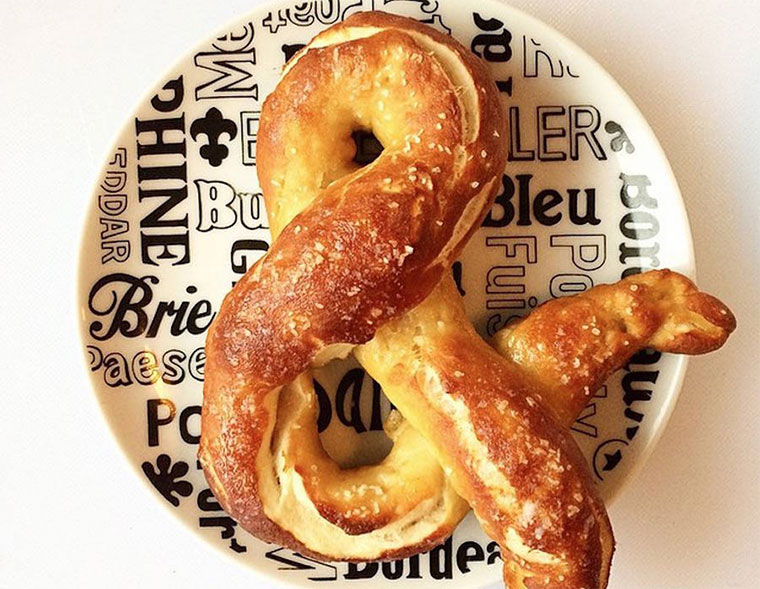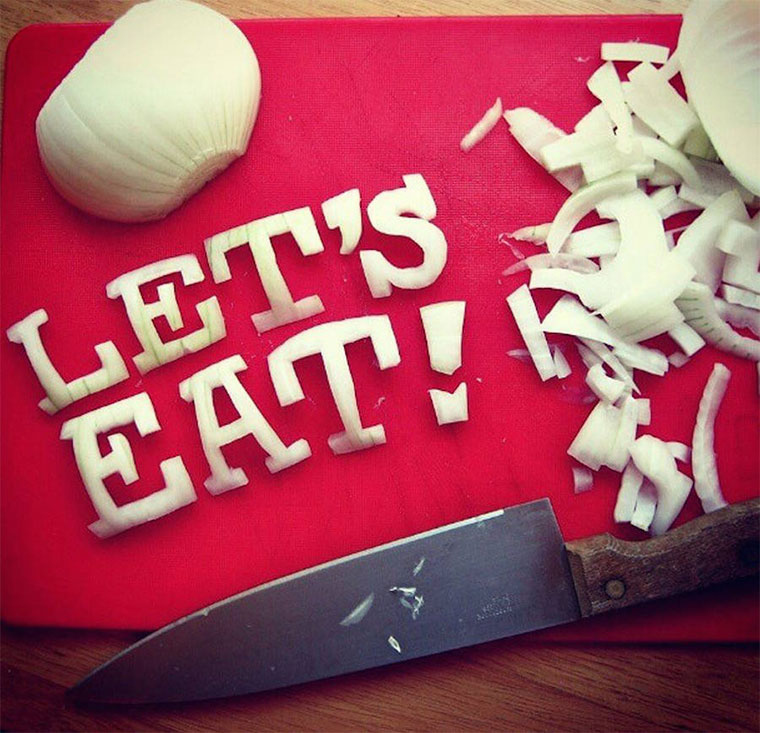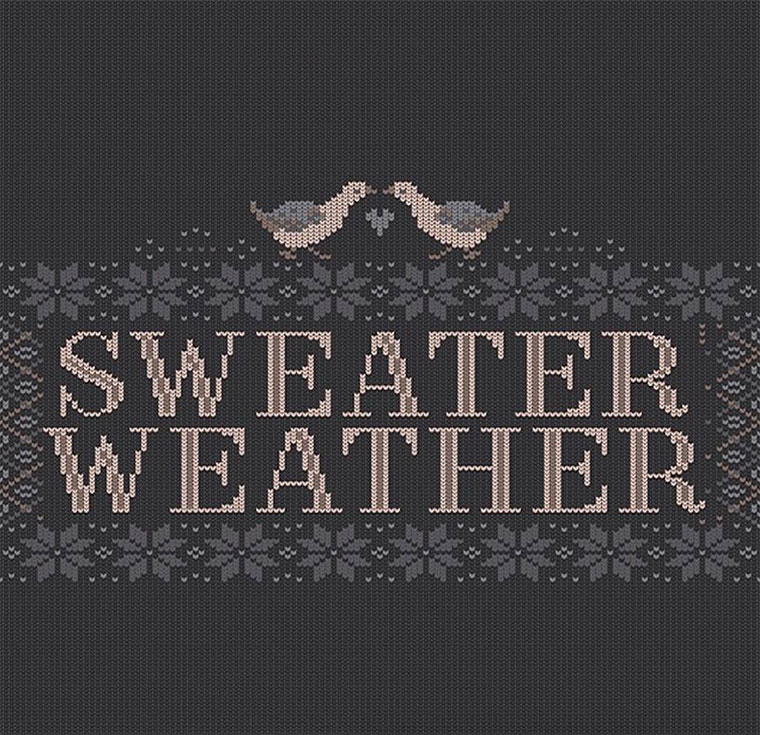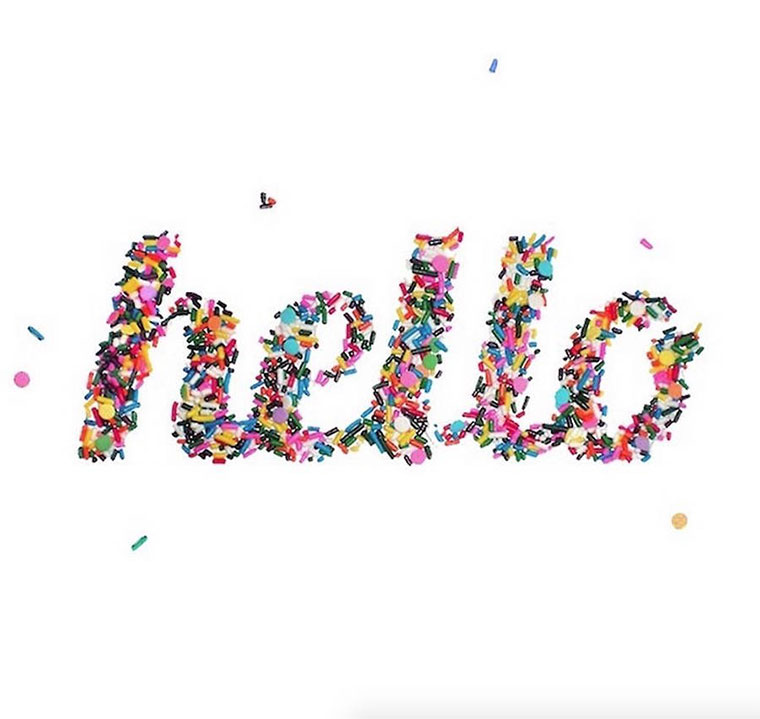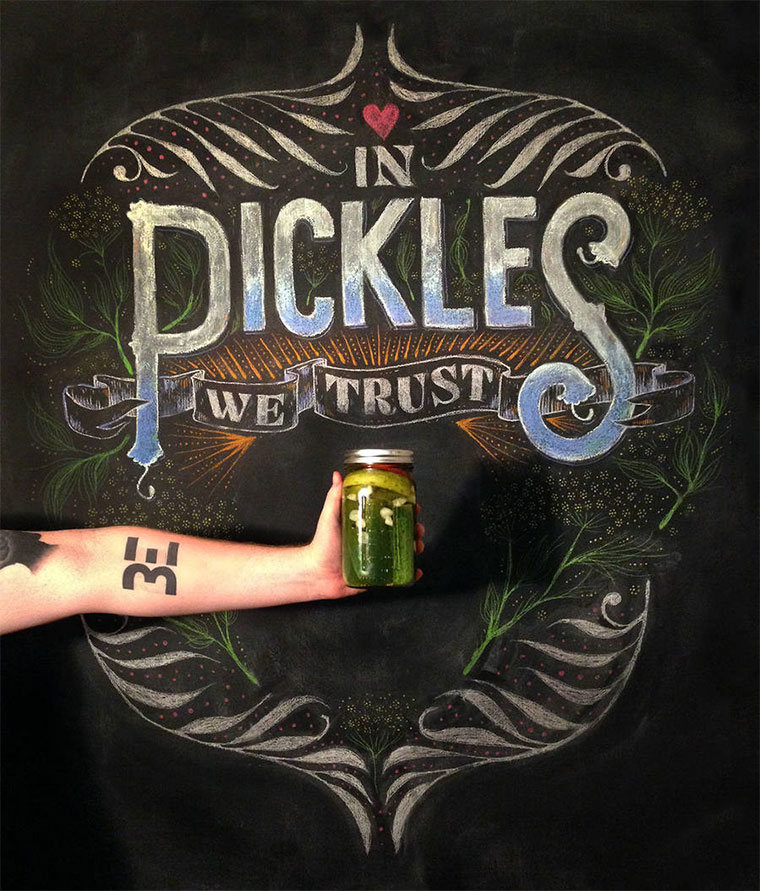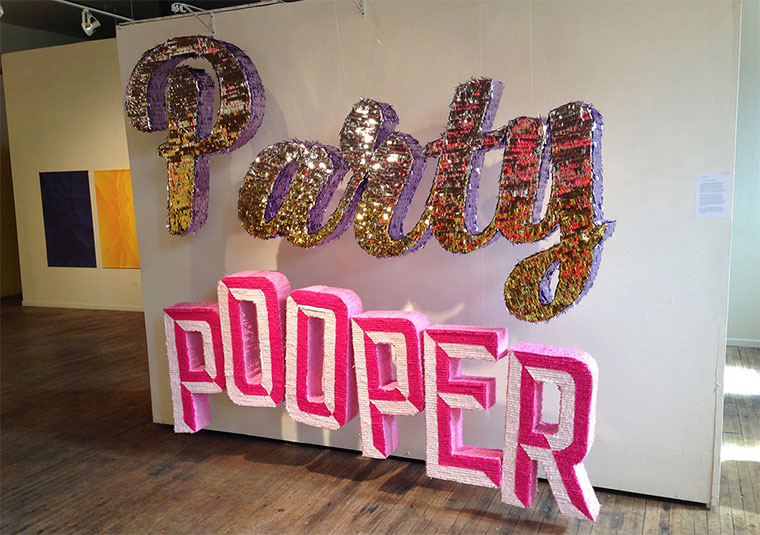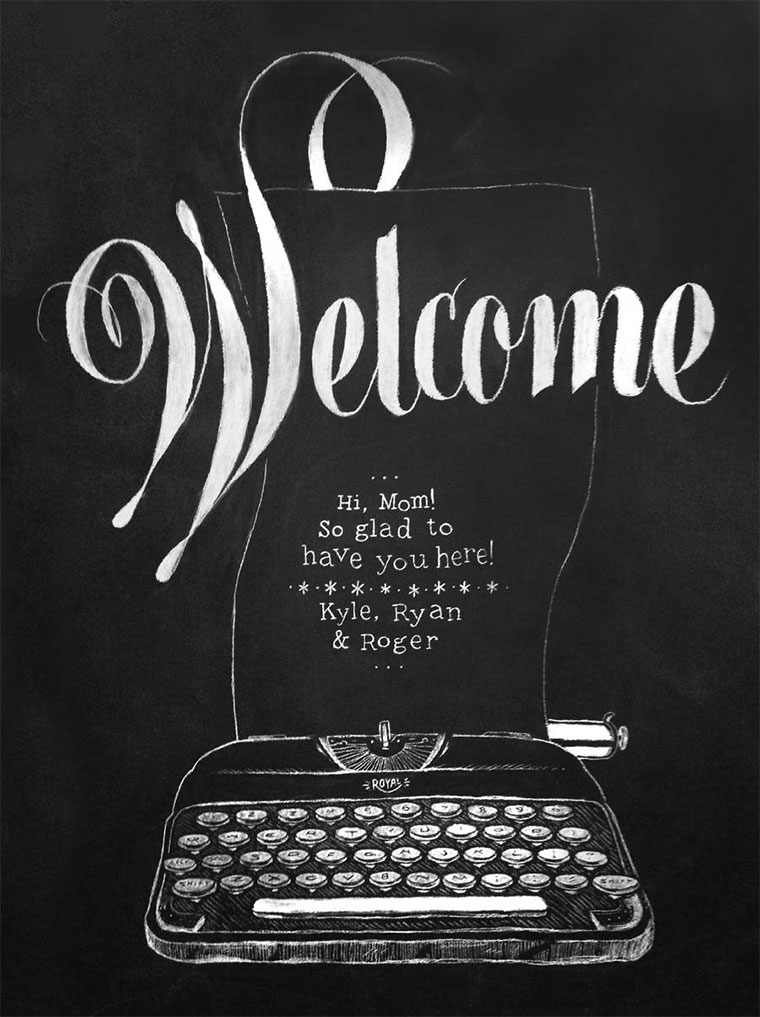
Lecker Lettering!
Typografie: Kyle Letendre
Buchstaben umgeben uns den ganzen Tag – du liest zum Beispiel gerade welche! Langweilige 08/15-Buchstaben im gängigen Pixel-Format… Kyle Letendre ist da deutlich origineller unterwegs. Der Illustrator aus Chicago macht aus allem Buchstaben und Worte, was er finden kann. Heraus kommen gebackene „&“, gestreute „Hellos“ und andere kreative Typografien.